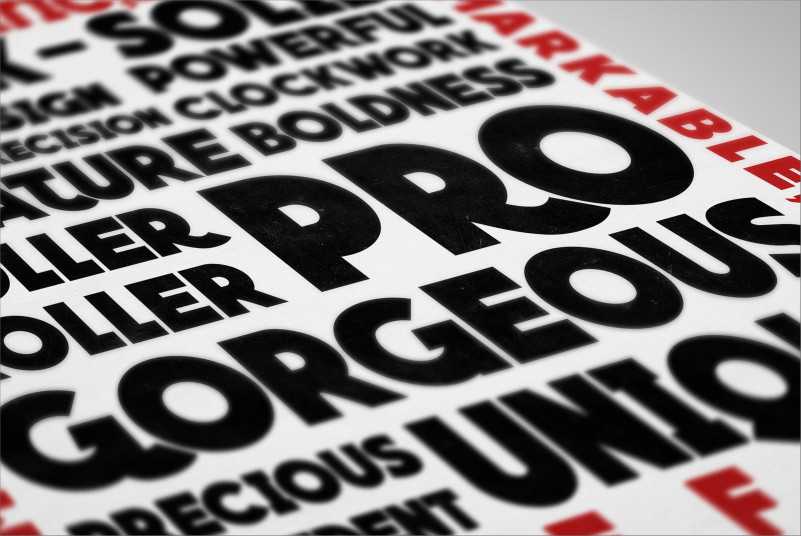
QUARTZO font – Download Grátis
A QUARTZO é uma fantasia tipográfica robusta que oferece belas ligaturas projetadas para destaque e headlines. Idealmente adaptada para ambientes onde se deseja um impacto imediato, esta fonte blackletter traz um toque de elegância e modernidade, perfeita para aplicações visuais variadas. Com estilos Regular e Light disponíveis no formato comercial, a QUARTZO é uma escolha ideal tanto para editoriais como para headlines em sites e mídias sociais, oferecendo o equilíbrio adequado entre força visual e graça artística. Ideal para designers e criativos que buscam uma alternativa única à tipografia comum, a QUARTZO se destaca como um recurso poderoso no arsenal de ferramentas gráficas do seu trabalho.